UDフォント(ユニバーサルデザインフォント)は、文字のかたちがわかりやすく、読みやすく、読み間違えにくいことをコンセプトに開発されました。文字情報を正確に伝えたい場面に効果を発揮するフォントです。和文以外にも、151言語をカバーする欧文書体や簡体字、繁体字、ハングル、アラビア文字、デーヴァナーガリー文字、タイ文字など、幅広く多言語にも対応しています。
UDフォント
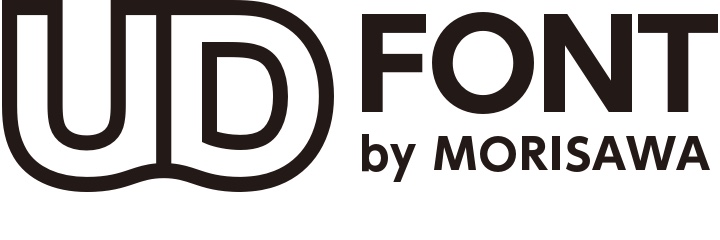
SDGsへの貢献
- 弱視や高齢者にも見やすい、読みやすいフォントを提供
- 読み書きが苦手なディスレクシアの子どもたちに配慮したフォントを教育現場に提供
- 各種文書・資料、プレゼンテーションや看板、公共物の情報を正しく分かりやすく伝える情報のユニバーサルデザイン化を支援
- 言語に関わらず、正しく情報提供ができるように文字情報の多言語化を支援
- 文章を読む速さの向上、誤読の削減によって、業務の効率化を支援